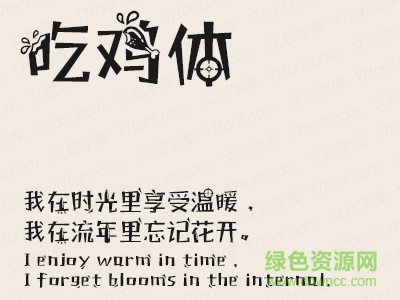
義啟吃雞體是一款義啟字體出品的簡(jiǎn)體超級(jí)字體,現(xiàn)在吃雞游戲非?;鸨?,怎么能沒(méi)有適合這款游戲的字體呢,大家可以使用這款字體聊天,增加游戲勝率喲。歡迎大家來(lái)綠色資源網(wǎng)下載使用!
義啟吃雞體,Winner winner,chicken dinner!There it is.